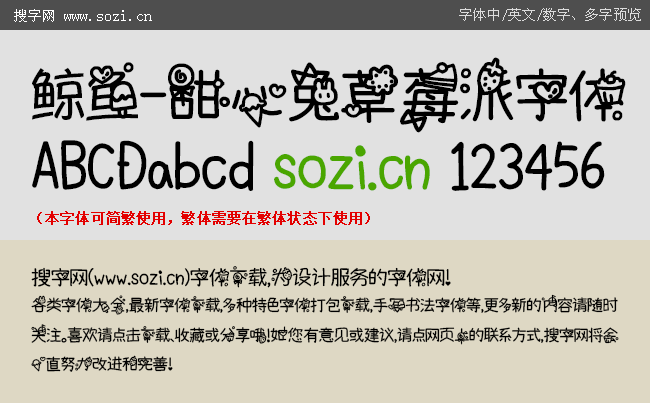
甜心兔草莓派字體
搜字網(wǎng)給大家提供一款卡通手寫(xiě)風(fēng)格的手機(jī)中文字體下載。名字叫甜心兔草莓派字體,這款手機(jī)字體是仿照兒童手寫(xiě)風(fēng)格的卡通手寫(xiě)字體,結(jié)構(gòu)帶有POP字體風(fēng)格,字體間還插入有趣的卡通圖案,特別適合喜歡手機(jī)字體個(gè)性一些的朋友在手機(jī)上安裝使用。